Hai un blog o un sito e sai benissimo come attrarre lettori: utilizzi le tecniche giuste sui social, scrivi contenuti interessanti e implementi le immagini e le infografiche più accattivanti. Eppure c’è un aspetto che molti blogger tralasciano e che, invece, richiede la massima attenzione in fase di start-up: quello della tipografia.
Con il termine “tipografia” qui intendo i principi base dell’arte della stampa che, però, possono essere utilizzati anche online: spaziature, formattazione, font, colore e grandezza dei caratteri sono elementi di fondamentale importanza per avere un blog o un sito non solo belli da vedere, ma che facilitano la lettura e quindi l’user experience della tua audience.
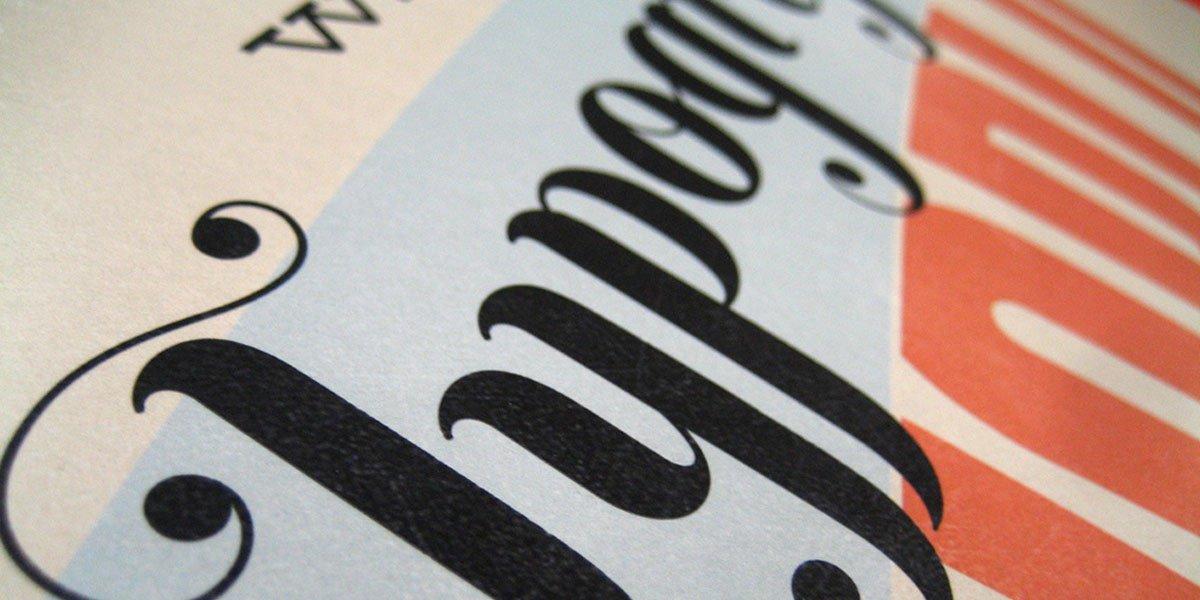
Un buon uso dei principi della tipografia, inoltre, può influenzare l’attenzione del lettore, dirottandola sui contenuti più importanti e facendo risaltare quelli che, nelle proprie intenzioni, devono godere di maggior visibilità.
Al contrario, una scelta di colori errata o persino il font non corretto possono rendere i tuoi post di difficile lettura, con conseguenze probabilmente nefaste: la scoperta della “Particella di Dio” fu messa un po’ alla berlina dal mondo dell’internet poiché i ricercatori hanno utilizzato l’odiato comic-sans come carattere della presentazione.
I cinque principi fondamentali della tipografia
Per non incorrere in problemi o, peggio, pericolosi epic fail, ecco alcune norme tipografiche che dovresti avere a mente per il tuo sito o blog:
- scegli un colore per il tuo font che contrasti con quello del tuo sfondo;
- evita i caratteri della famiglia Serif;
- tieni a mente cosa vuoi comunicare (la tua mission, il tuo tone of voice) quando scegli il font;
- non esagerare con il numero di font su pagina;
- considera sempre l’user experience del tuo lettore, soprattutto da mobile.
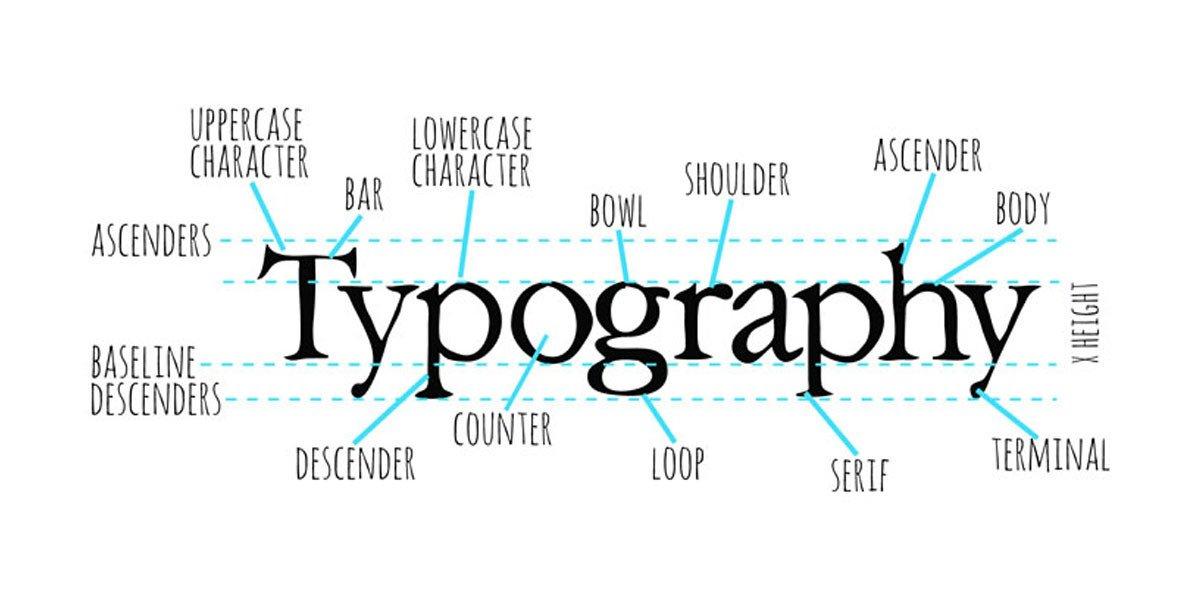
Le migliori risorse online
Se non sei un esperto web designer o un maestro dell’user experience, non disperare. Ci sono alcune risorse online che possono aiutarti nella scelta del giusto font o a capire come migliorare gli elementi tipografici del tuo sito.
WhatTheFont di MyFont, ad esempio, ti permette di identificare il font utilizzato in un’immagine. Hai visto un sito web che utilizza un carattere che reputi particolarmente gradevole ma non riesci a riconoscerlo? Basta fare uno screenshot e caricarlo su WhatTheFont per scoprire qual è e magari utilizzarlo per la tua pagina.
Se hai centinaia di font a disposizione sul tuo pc ma non sai quale usare, prova a usare Font Picker: questo semplicissimo tool ti aiuterà a catalogare e organizzare la tua libreria di caratteri per poter scegliere poi quello più adatto con comodità.
Google Fonts è un’altra utilissima risorsa. La pagina è infatti un’enorme raccolta di font open-source da utilizzare per ogni tuo progetto online. Con i vari filtri e slider è possibile provare numerosi caratteri, osservare il loro rendimento con una frase da te scelta e scegliere il font più adatto alle tue esigenze: tutti i font presenti sono gratuiti e perfettamente ottimizzati sia per il web tradizionale che per il mobile.
Anche TypeWonder è molto utile. Il sito infatti ti permette di visualizzare come diversi font si adattano alla tua pagina o al tuo blog, senza fare modifiche su modifiche: basta incollare la tua URL su TypeWonder e poi scegliere i font da testare, fino a scegliere quello che più risponde alle tue necessità. Facile e rapido da utilizzare, Typewonder inoltre propone anche delle estensioni per browser in grado di renderlo ancora più comodo e potente.
Se hai già in mente il font primario per il tuo sito ma non sai quali font secondari abbinare, TypeGenius è la risorsa che fa per te. Dalla sua home page, scegli il tuo carattere di riferimento: TypeGenius ti proporrà i migliori abbinamenti con altri font, tutti corredati da immagini e testi di riferimento per darti subito un utile riscontro visivo.
È insomma ovvio che i contenuti - sia grafici che testuali - siano fondamentali per il buon successo di un sito o un blog. Ma senza la giusta formattazione e attenzione alla tipografia anche l’articolo più completo e autorevole rischia di finire nel dimenticatoio o, peggio, non letto.
E tu, quale font utilizzi nella tua attività online?